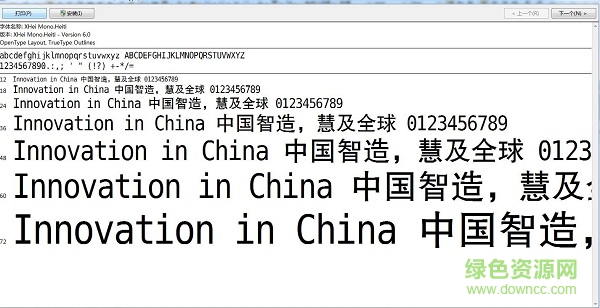
xhei mono字體是一款簡潔干凈的黑體字體,線條流暢,筆畫粗細(xì)均勻末端不尖,視覺感受較佳,非常易于易于閱讀,移動設(shè)備上通常使用這類字體,需要的朋友歡迎綠色資源網(wǎng)免費(fèi)下載!
1.宋體字的字體更像是用筆書寫出來的,這種字體的手寫體的感覺更強(qiáng)烈,多用于文字量較大,有希望讀者能夠平靜閱讀下去的文章中。
2.宋體字也被認(rèn)為是具有歷史感的字體,而且雖然通常認(rèn)為“當(dāng)排版較大的標(biāo)題是最好選用黑體”但是如果大標(biāo)題選用宋體排版,就會產(chǎn)生出不同的高雅趣味。
3.相對于宋而,黑體字的橫豎筆畫的粗細(xì)要相對一直,“人工設(shè)計”的效果也更強(qiáng),常被用于作為“力量較強(qiáng)的效果”和“時尚的效果”的處理 。
4.標(biāo)題如果選用黑體來處理,會比宋體更容易給人帶來較為強(qiáng)烈的印象,因此黑體字的直觀效果相對于宋體等手寫體來說要更強(qiáng)一些。